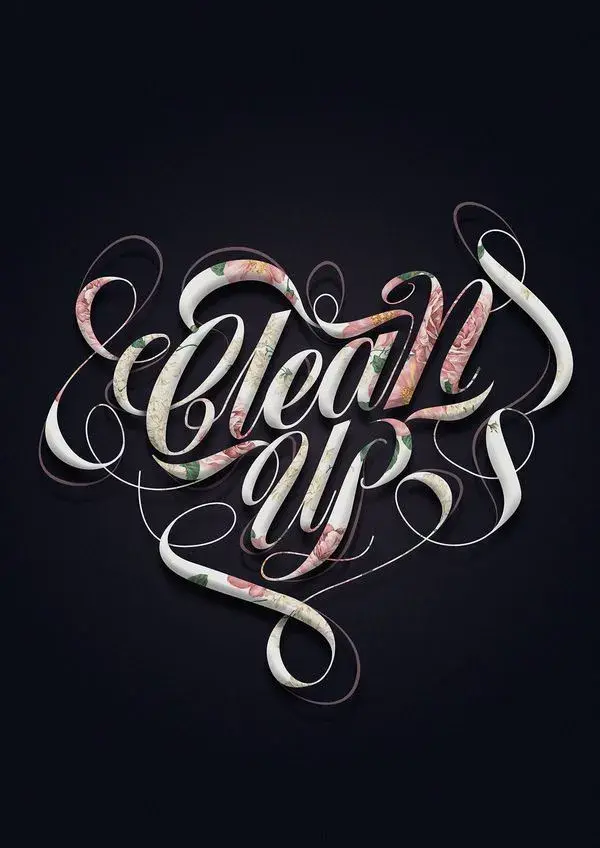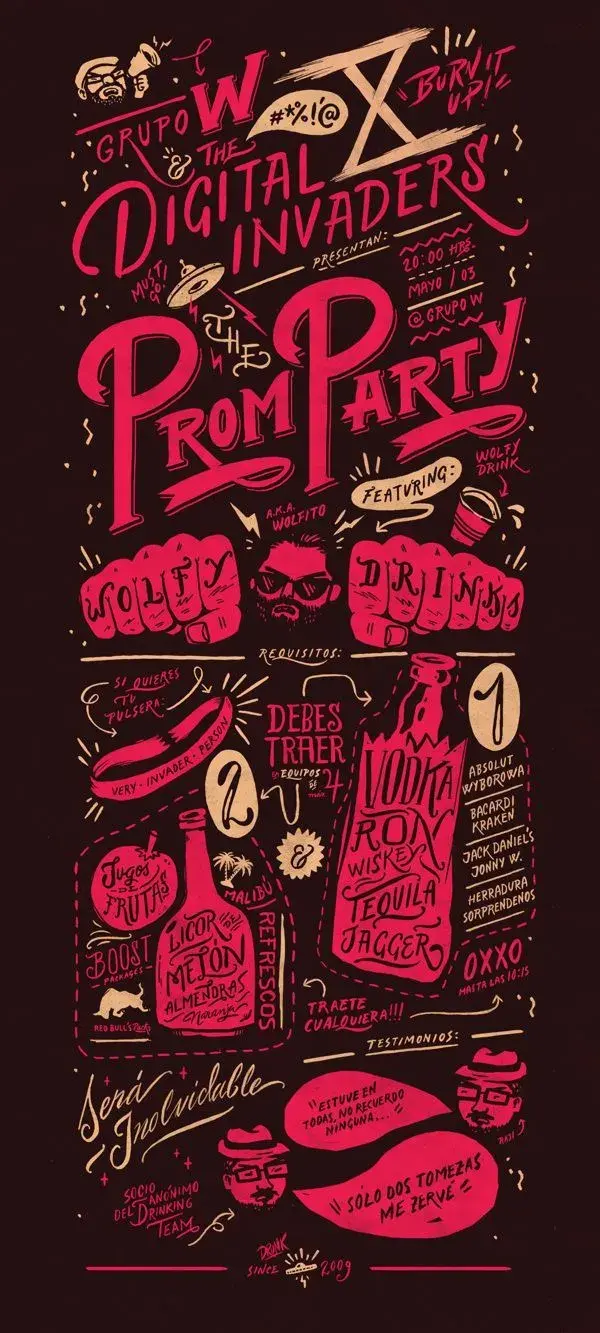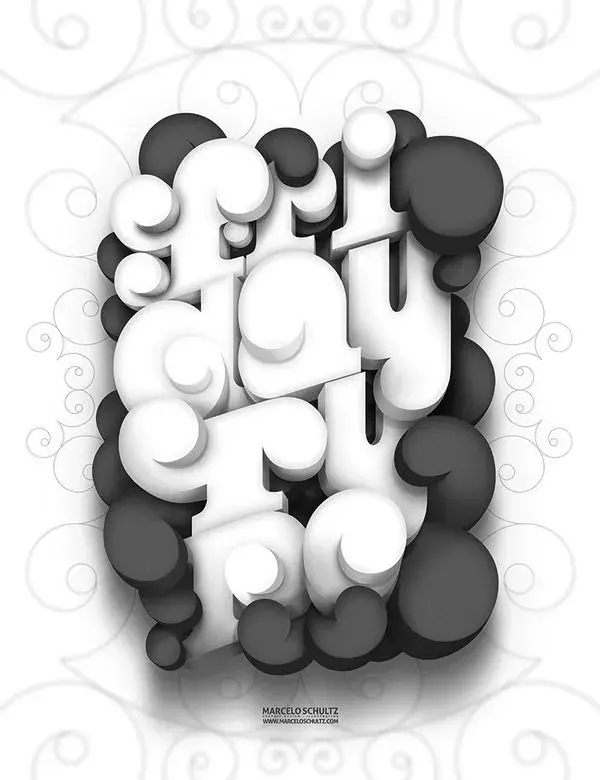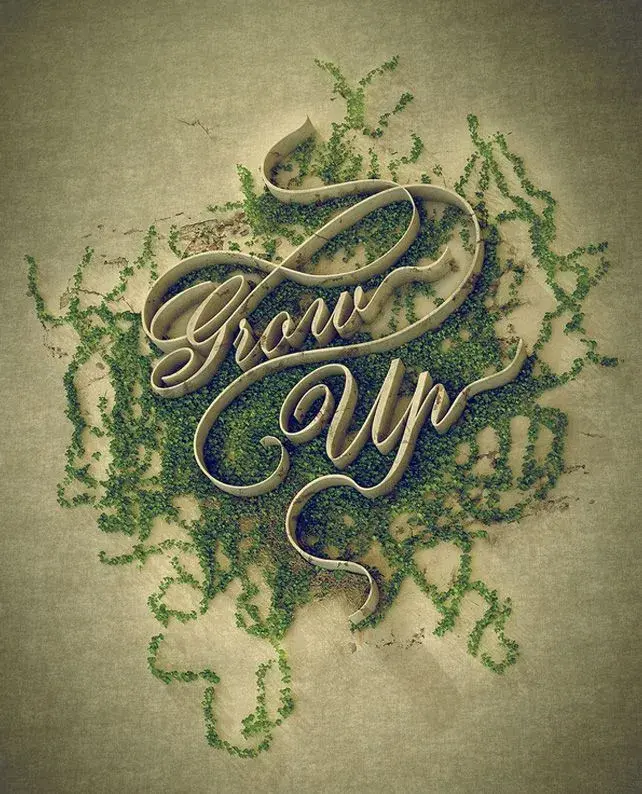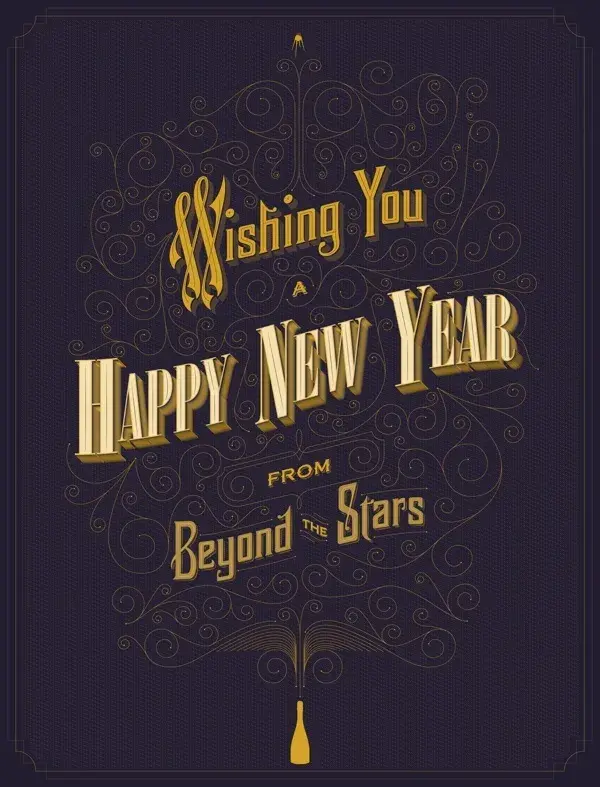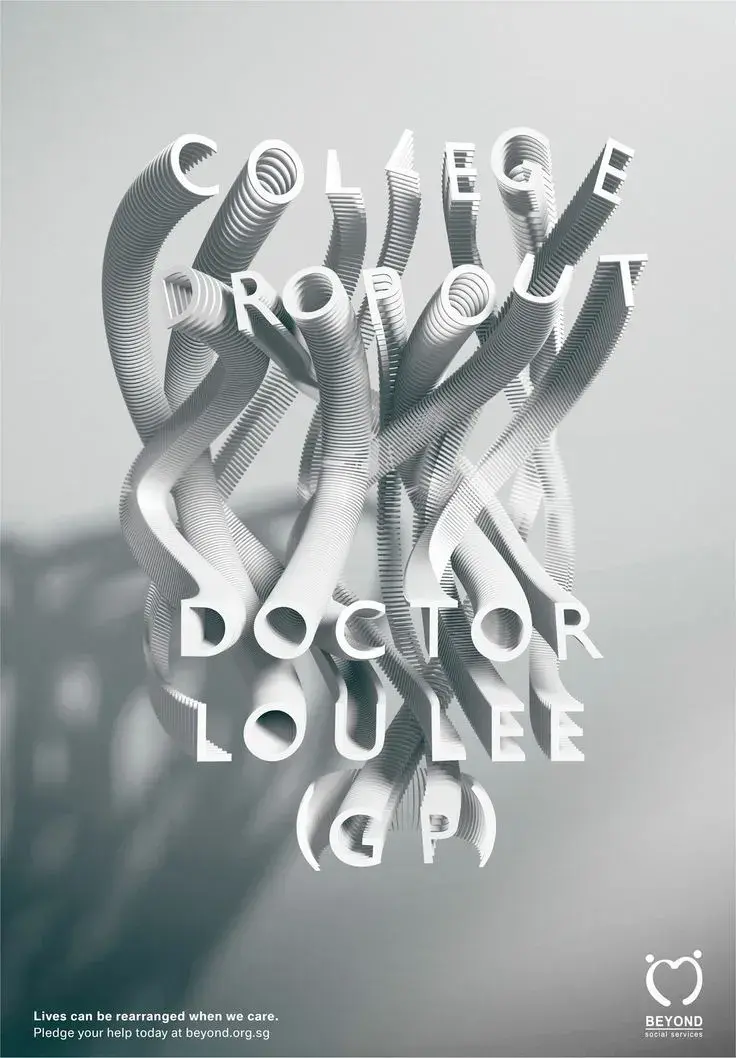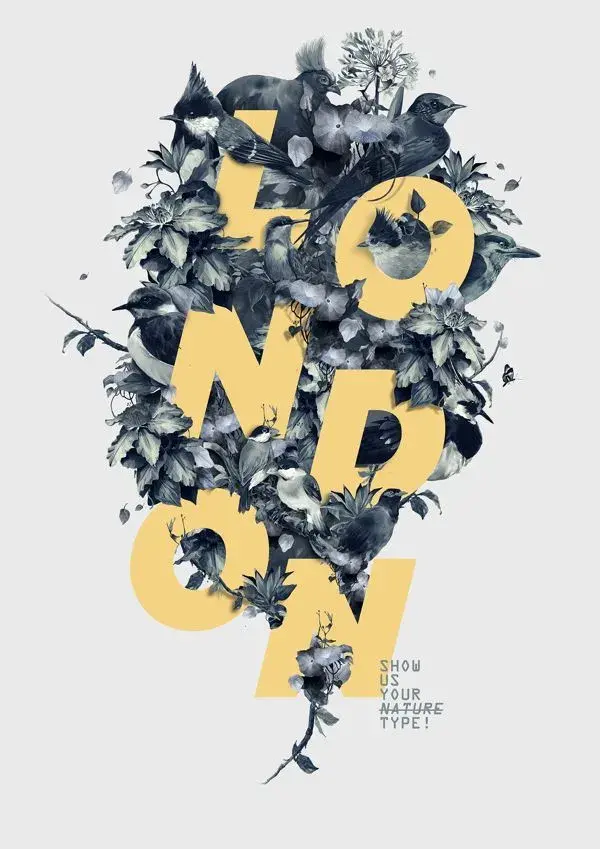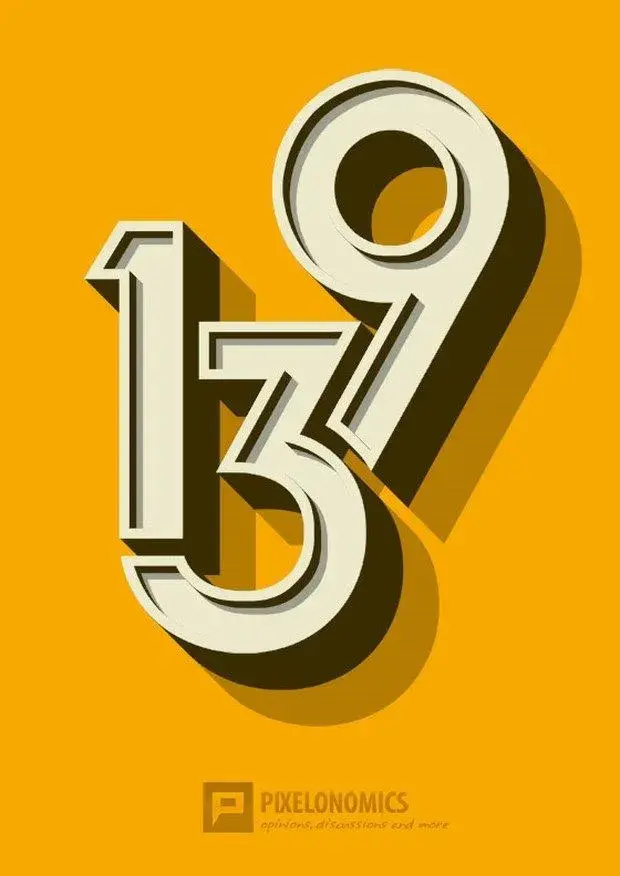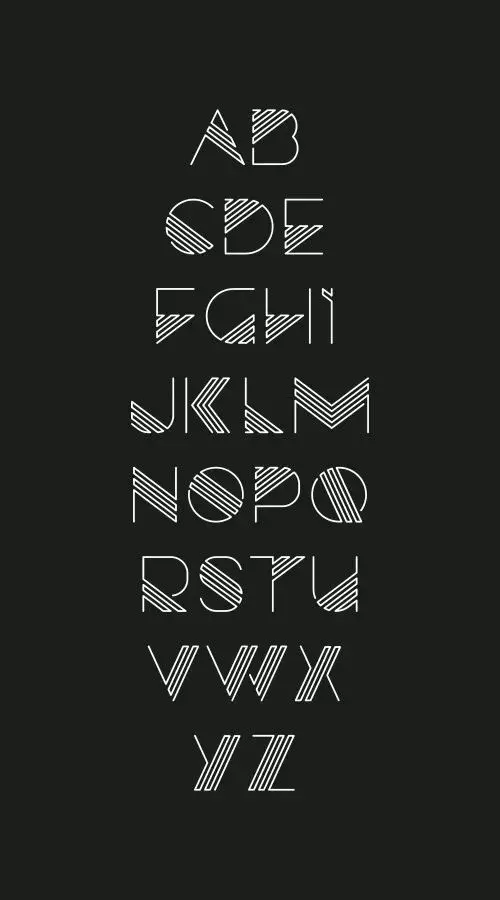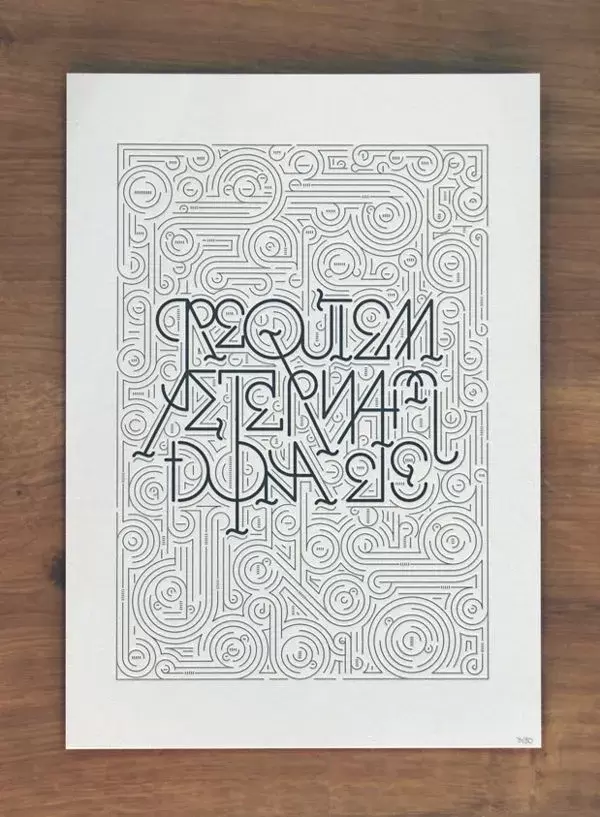
Créations graphiques et typographiques inspirantes | Affiches, posters et projets originaux
30 créations autour de la typographie et du graphisme
Nous avons rassemblé différentes créations autour de la typographie avec une sélection d’affiches de poster et de projets originaux.
Vous pourrez découvrir un mélange de styles graphiques utilisant la typographie, la calligraphie et le lettrage afin de vous donner une dose d’inspiration pour vos prochaines créations, ou simplement voir de belles réalisations.